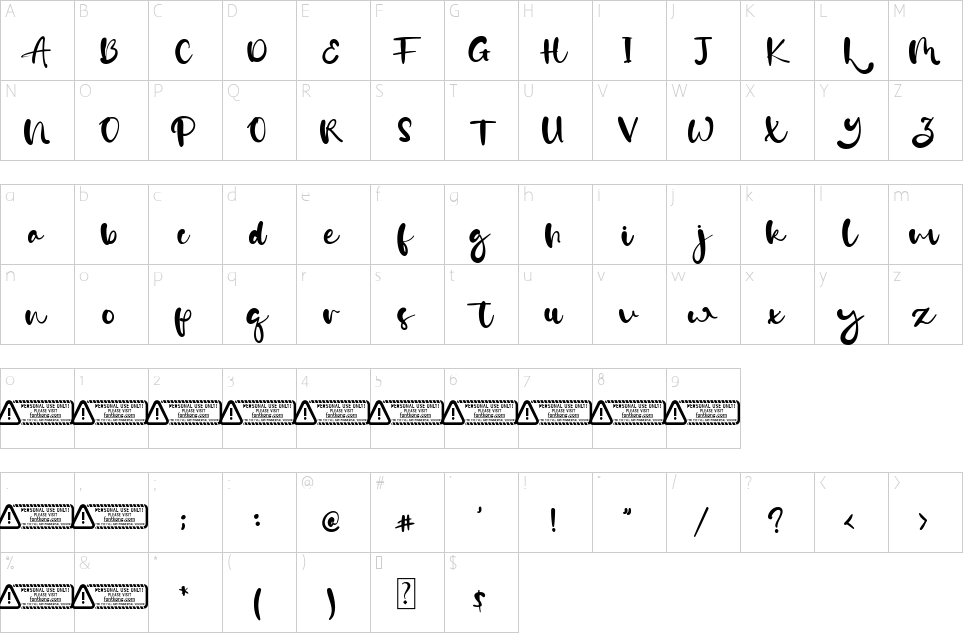
A Mary Boyd font é um recurso gratuito disponível para download, criada pelo Font Kong. Essa fonte elegante e delicada é perfeita para quem busca um estilo único para seus projetos digitais. Com seu design cuidadosamente elaborado, a Mary Boyd traz uma atmosfera envolvente e natural às suas criações. Esta fonte está disponível tanto para Windows quanto para Mac, facilitando a sua implementação em qualquer dispositivo. Com mais de mil downloads, é evidente que muitos usuários encontram a Mary Boyd font versátil e de alta qualidade. Se você está em busca de uma fonte para adicionar a sua biblioteca, a Mary Boyd font é uma opção que vale a pena explorar.